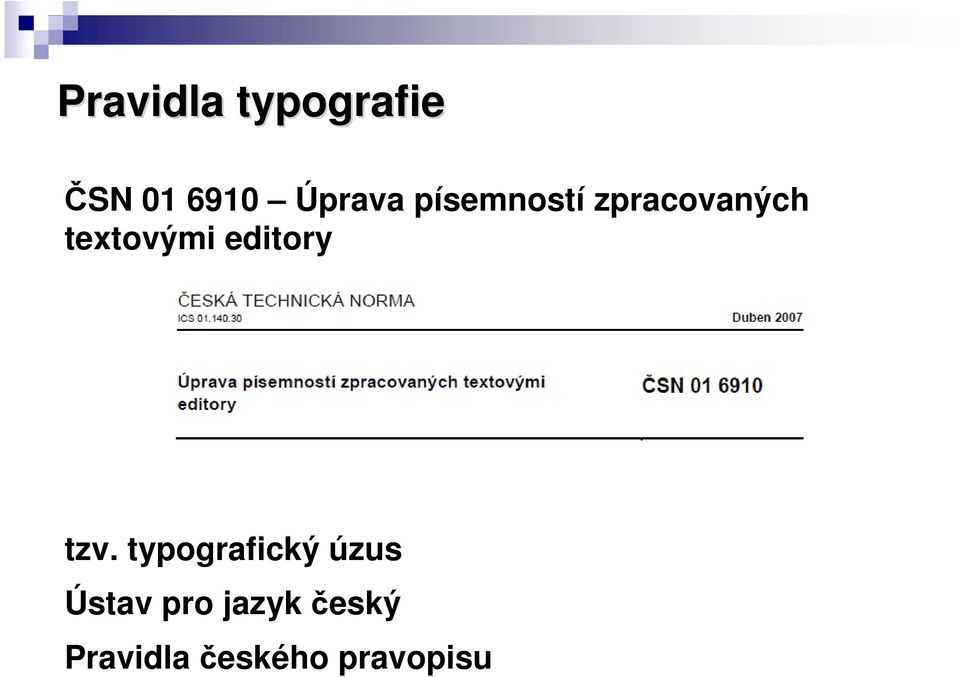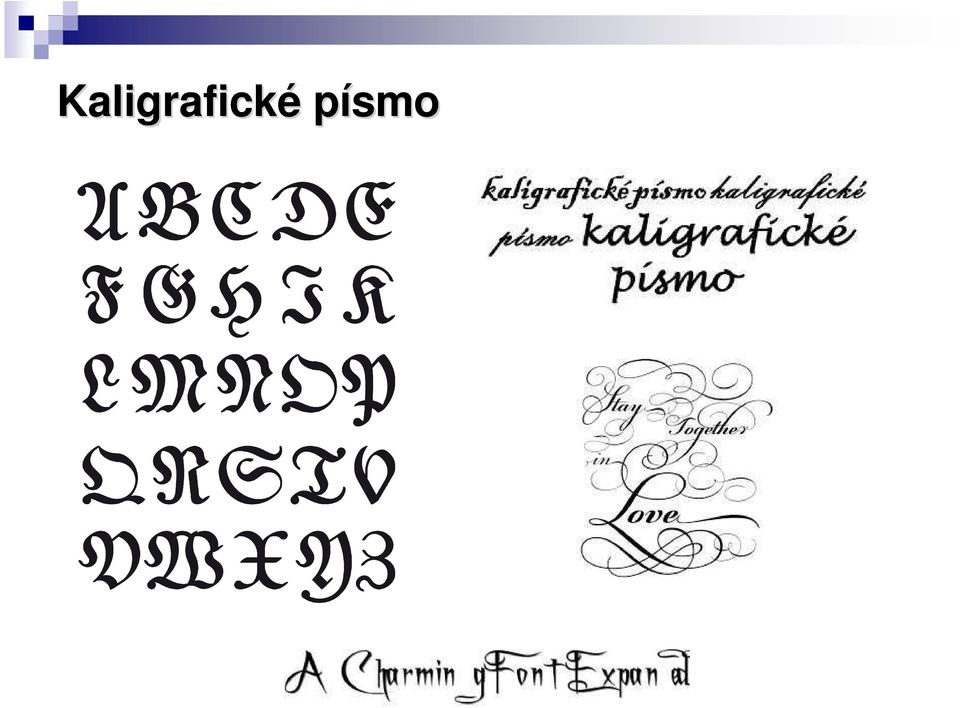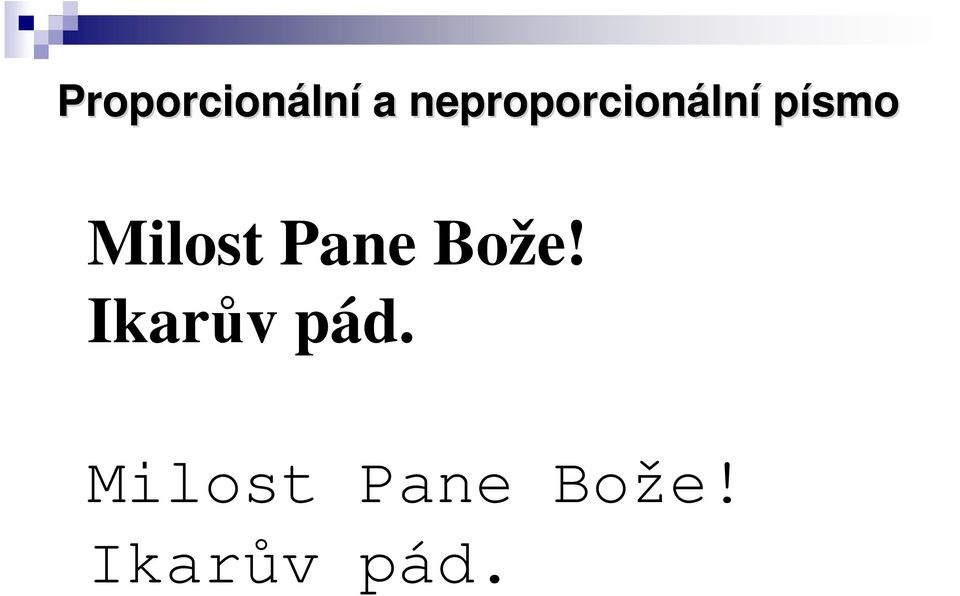
2 Motto: Profesionální dokument (web) musí být správně nejen gramaticky, ale i typograficky.
3 Typografie je umělecko-technický obor, zabývající se písmem, především jeho správným výběrem, použitím a sazbou. Slovo typografie se skládá ze dvou slov: typus (lat.) = znak a grafó (lat.) = píši.
4 Typografie je nauka o tom, jak má vypadat správně upravený text. Dodržení typografických pravidel má zajistit: snadnou orientaci, dobrou čitelnost, estetické působení, jednotnost. V minulosti klasické umělecké řemeslo knihtisk (od roku 1440). Dnes počítače píše a tiskne kdokoli.
5 Pravidla typografie ČSN Úprava písemností zpracovaných textovými editory tzv. typografický úzus Ústav pro jazyk český Pravidla českého pravopisu
6 Písmo
7 Patkové versus bezpatkové písmo Times New Roman Courier New T Arial Verdana T
8 Kaligrafické písmo
9 Proporcionáln lní a neproporcionáln lní písmo Milost Pane Bože! Ikarův pád. Milost Pane Bože! Ikarův pád.
10 Neproporcionáln lní písmo Využití v praxi: text na psacích strojích, tisk do tiskopisů, programovací jazyky, číselné sestavy,
11 Neproporcionáln lní písmo 1.880,- Kč 110,- Kč 560,- Kč 7,- Kč
12 Neproporcionáln lní písmo Písmo Courier New ,- Kč ,- Kč ,- Kč 7,- Kč Písmo Trebuchet ,- Kč ,- Kč ,- Kč 7,- Kč
13 Druh písma p a řez písmap Times New Roman TrebuchetMS Verdanatučná Verdanakurziva Verdanapodtržená
14 Písmo Toto je písmo Garamound; nejoblíbenější písmo českých a zahraničních typografů. Toto je písmo Helvetica; druhé nejoblíbenější písmo českých a zahraničních typografů. zdroj: a
15 Český typograf Tomáš Brousil
16 Typografická pravidla
17 Pevná mezera <Ctrl> + <Shift> + <mezerník> Prof. MUDr. Mokroš, Ing. Tomáš Kostka Zahrajte mi tu skladbu č. 3 v E dur. 10 cm, 9, , s. r. o., v Havířově, n. l , , Otec & syn PM po předložkách: K, k, S, s, V, v, Z, z, O, o, U, u PM po spojkách: A, I, i U spojky a není PM povinná.
18 Interpunkční znaménka nka Tečka, čárka, dvojtečka, středník, vykřičník, otazník Čalouníme nábytek. Chcete si vybrat látku? Obraťte se na nás! Děkuji. KAKTUS, spol. s r. o., Ústí n. Orl., Východočeský kraj Inzertní rubriky se týkají výměny bytů, nabídky služeb apod. funkce: sinus, kosinus a tangens
19 Interpunkční znaménka nka Tečka bez mezery Mgr. Ivana Bendová, Ph.D Kč vysledky.xls kapitola Tečka se nepoužívá u nadpisů, popisů obrázků a titulků, které stojí na samostatném řádku, lze ji použít, pokud nadpis není samostatně graficky oddělen.
20 Interpunkční znaménka nka Tři tečky = výpustka Opravujeme domácí elektrické spotřebiče, jako ledničky, pračky, všechny další připomínky jsou oprávněné. Doplň scházející: leden, únor,, duben, květen. Větná tečka se za výpustku již nepíše. výpustka <Alt >
21 Interpunkční znaménka nka Pomlčka, a spojovník - Internet byl původně vytvořen a používán k rychlému a bezpečnému sdělování informací nejprve pro armádu a teprve později se ho začalo používat také ve vědeckých a vzdělávacích institucích. dálnice Praha Brno; trať Ostrava Frýdek-Místek Střední škola, Havířov-Šumbark Střední škola, Havířov Prostřední Suchá literárně-hudební obor; zemědělsko-lesnické otázky; Praha-Vinohrady; Praha 10 Zahradní Město
22 Interpunkční znaménka nka Pomlčka ve významu od do, až, versus, a válka ; školní rok ; působil ve sboru v letech ; strana ; skončili na místě; knihu napsala dvojice Ptáček Koniklec Pomlčka není na klávesnici, píšeme pomocí <Ctrl + mínus> na numerické klávesnici nebo <Alt >. Při grafickém zpracování vývěsních tabulí, ceníků apod. lze tolerovat i pomlčku s mezerami.
23 Interpunkční znaménka nka Pomlčka ve významu od do, až, versus, a Vyhráli Kč. V třináctém kole se utkalo Brno Olomouc. V třináctém kole se utkalo Brno Uherské Hradiště. Knihu napsala dvojice Kostka Chmiel. Knihu napsala dvojice Tomáš Kostka Pavel Chmiel.
24 Interpunkční znaménka nka Pevný spojovník nechtěné dělení Pevný spojovník - <Ctrl> + <Shift> + <pomlčka> Přesný název naší školy: Střední škola, Havířov- Šumbark, Sýkorova 1/613, příspěvková organizace. Přesný název naší školy: Střední škola, Havířov-Šumbark, Sýkorova 1/613, příspěvková organizace. , e-cigareta, e-komunikace, e-strava,
25 Interpunkční znaménka nka Závorky Pro děti od šesti do deseti let jsou vhodné stolní hry (fotbal, kulečník). Slovní zásoba se neustále mění, protože jazyk jako nástroj dorozumění se přetváří zároveň s vývojem společnosti. [5] Souřadnice bodu A jsou [ 3,4]. < Množina C obsahuje prvky A a B, tedy C = {A,B}.
26 Interpunkční znaménka nka Lomítko 60 km/h; čj. Pa/3456/07; faktura č. 2059/02; školní rok 2007/08 Vážená paní/vážený pane, Údaje uvedené v záhlaví/v zápatí Informace najdeš na Turgeněvova 120/52, Havířov-Město Vypočítejte a výsledek zapište do tabulky.
27 Interpunkční znaménka nka Uvozovky Ředitelka mateřské školy říká: Dětem nechybějí věci, ale vztahy. Správná hračka podporuje přirozenou touhu všech dětí přicházet věcem na kloub. Miloš Ondráček napsal: Rytcův projev při tvorbě známky musí souznít se záměrem výtvarníkovým. Ke zrušení probíhající funkce se v programu používá klávesa <Esc>.»Jdu domů,«oznámil.